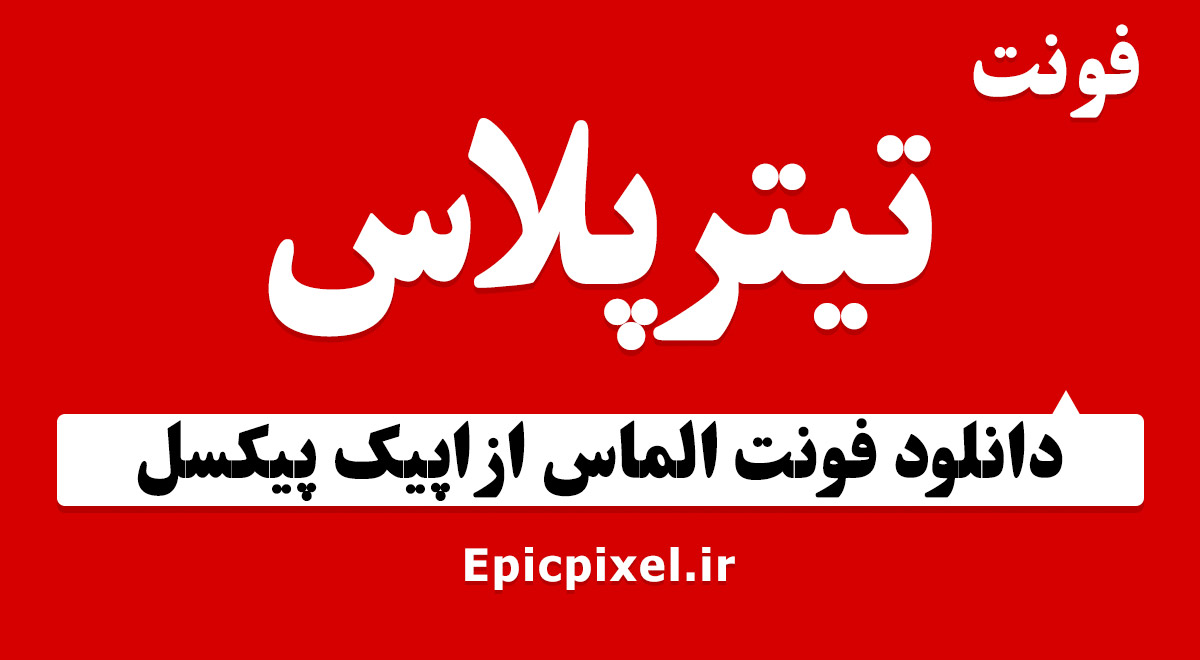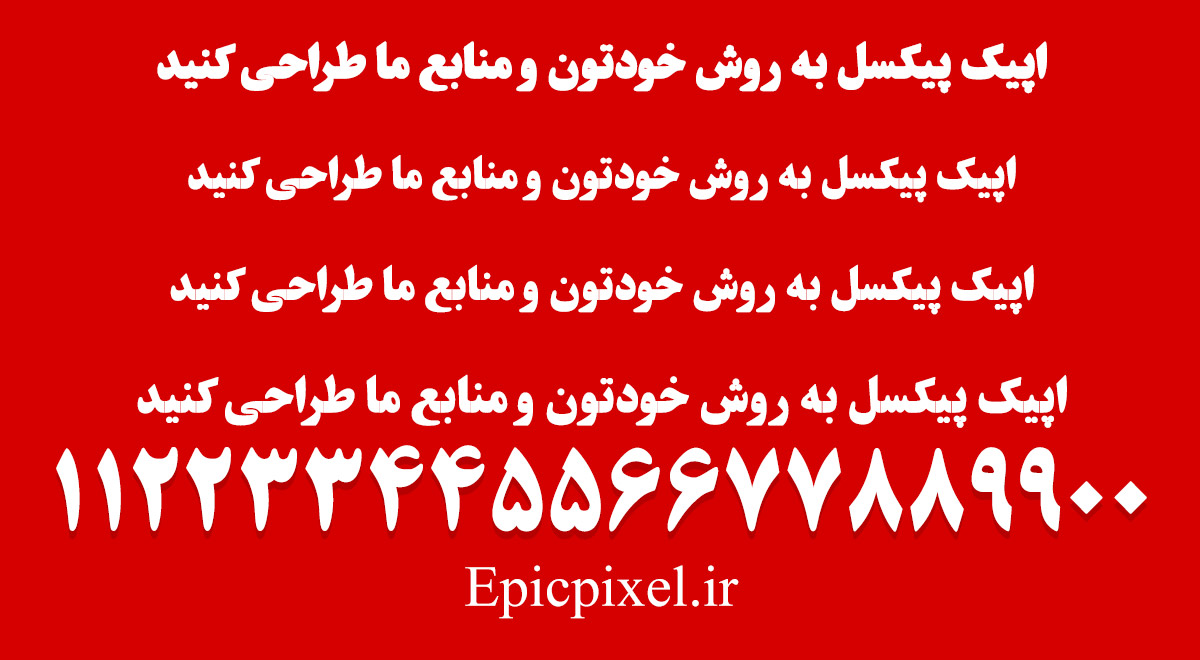
3 فونت تیترپلاس فارسی
سلام وقتتون بخیر من فونت black همین فونت یعنی بولد ترین حالتش رو بخوام از کجا باید تهیه کنم؟؟
سلام در سه حالت مختلف منتشر شده که به اسم بولد هست ولی کاملا ضخیمه .بیشتر از این ساخته نشده . ولی اگه جایی مشاهده کردید لینک بفرستید بررسی میشه
خیلی خوبه حالا از سه تاش یکی اش که تیتر معمولی محسوب میشه ولی واقعا اون دو تا عالیه عالی عالی مخصوصا لاین که دیگه محشره